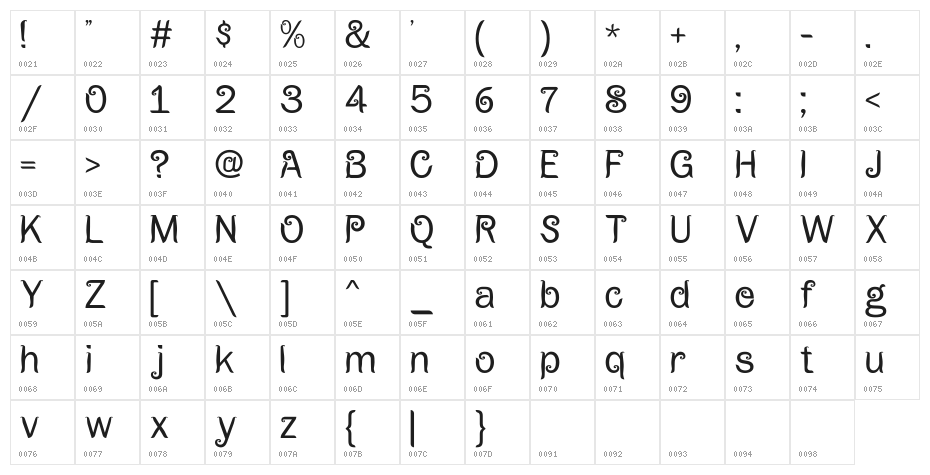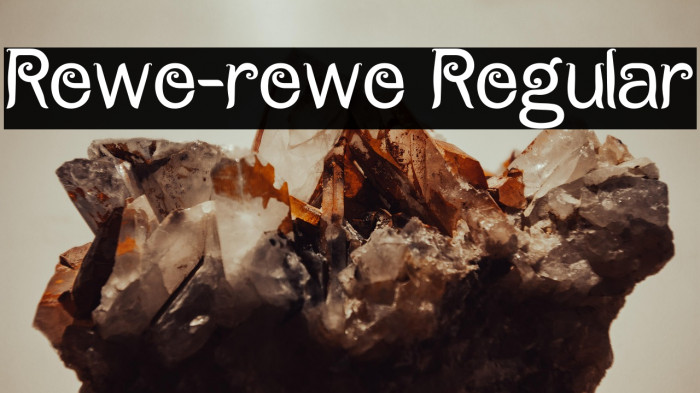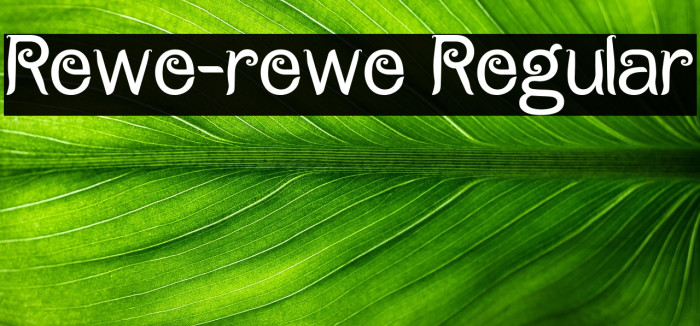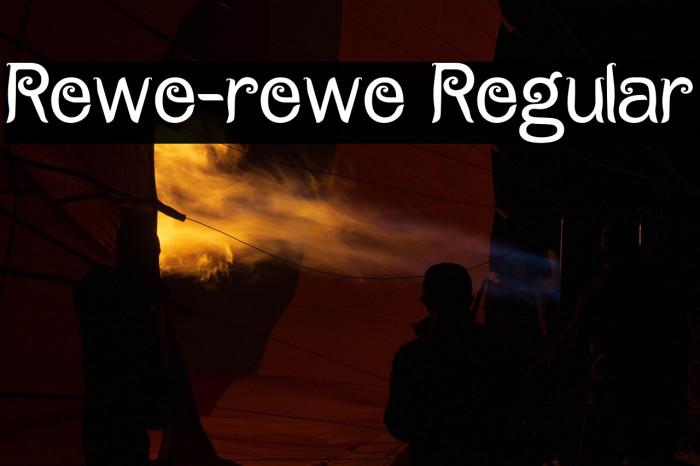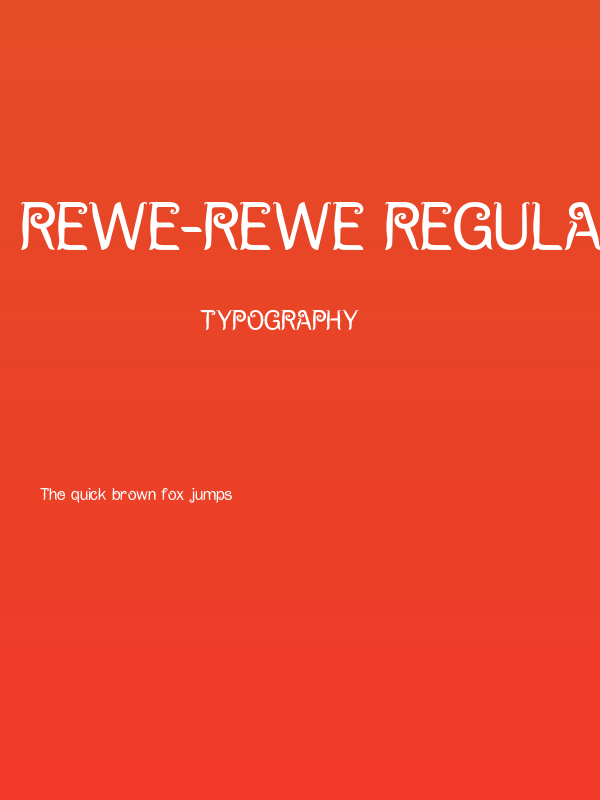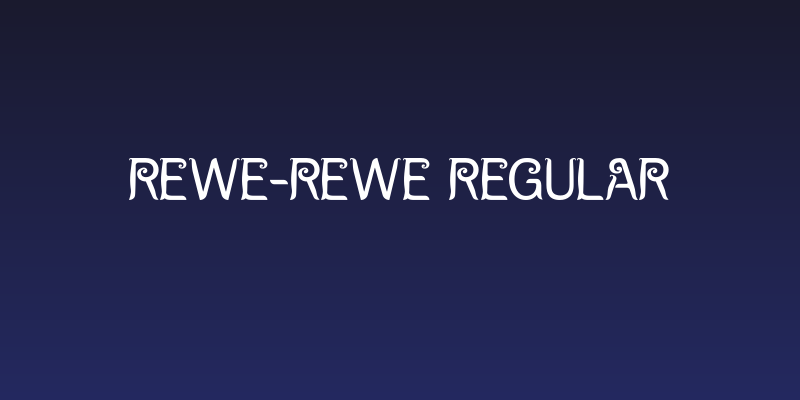
Rewe-rewe Regular Font
✎ Curly
| Categorie | Curly |
| Stile generale | Playful, Artistic |
| Caso d'uso | Headlines, Logos, Creative projects |
| Progetti proposti | Ideal for children's books, creative posters, playful branding, and artistic invitations. |